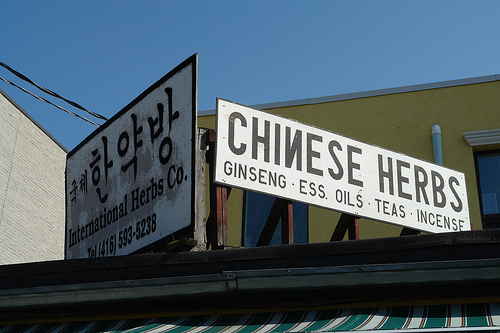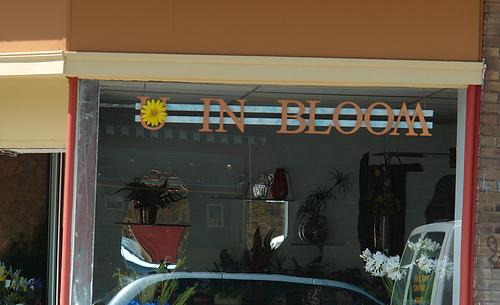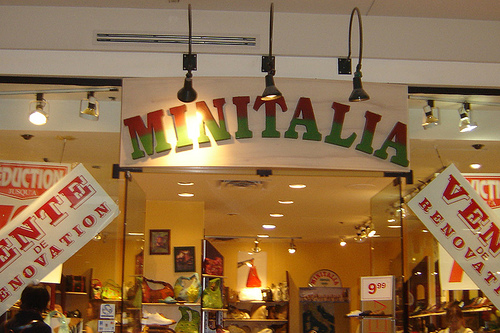
It´s a fine line between I and J...
Beobachtet mal die Strassenschilder – kaum zu glauben. Bei Gelegenheit zeig ich Euch ein seitenverkehrtes Versal-A.
die blauen straßenschilder sind sowieso die schlimmsten. die machen die städte alle selber und nutzen die schriften die sie dafür haben, imes, fette fraktur, schwabacher usw. alles schon gesehen. schlimm! wir brauchen NORMEN, viel mehr NORMEN. :twisted:
nein! quatsch, also ich mag das. bunte schilderhaufen ist doch viel interessanter. stellt euich mal vor jedes schild würde gleich aussehen, wie laaaangweilig.
stellt euich mal vor jedes schild würde gleich aussehen, wie laaaangweilig.
Nun, ich glaube man würde sich nicht mehr zurecht finden. :twisted: